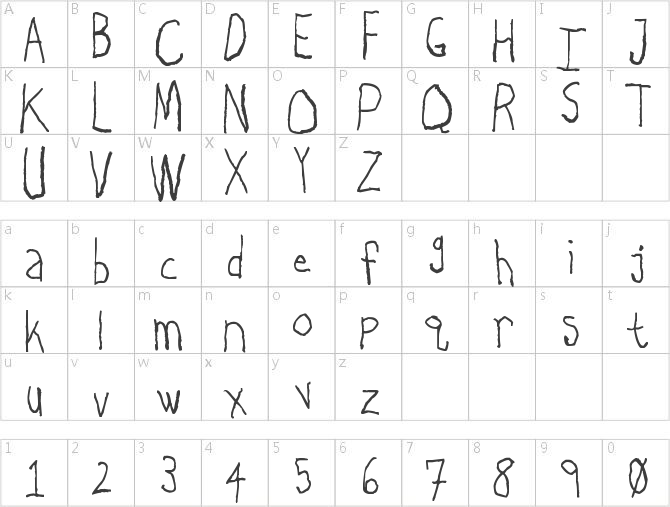
Lefty Does Righty Charcoal
Lefty Does Righty Charcoal介绍
Lefty Does Righty Charcoal字体字库是一款让人赏心悦目、百看不厌的英文字体,适合各类广告和产品包装设计应用,字体大小0.02MB,格式为ttf字体,上传用户是Honor,作者/版权方为未知